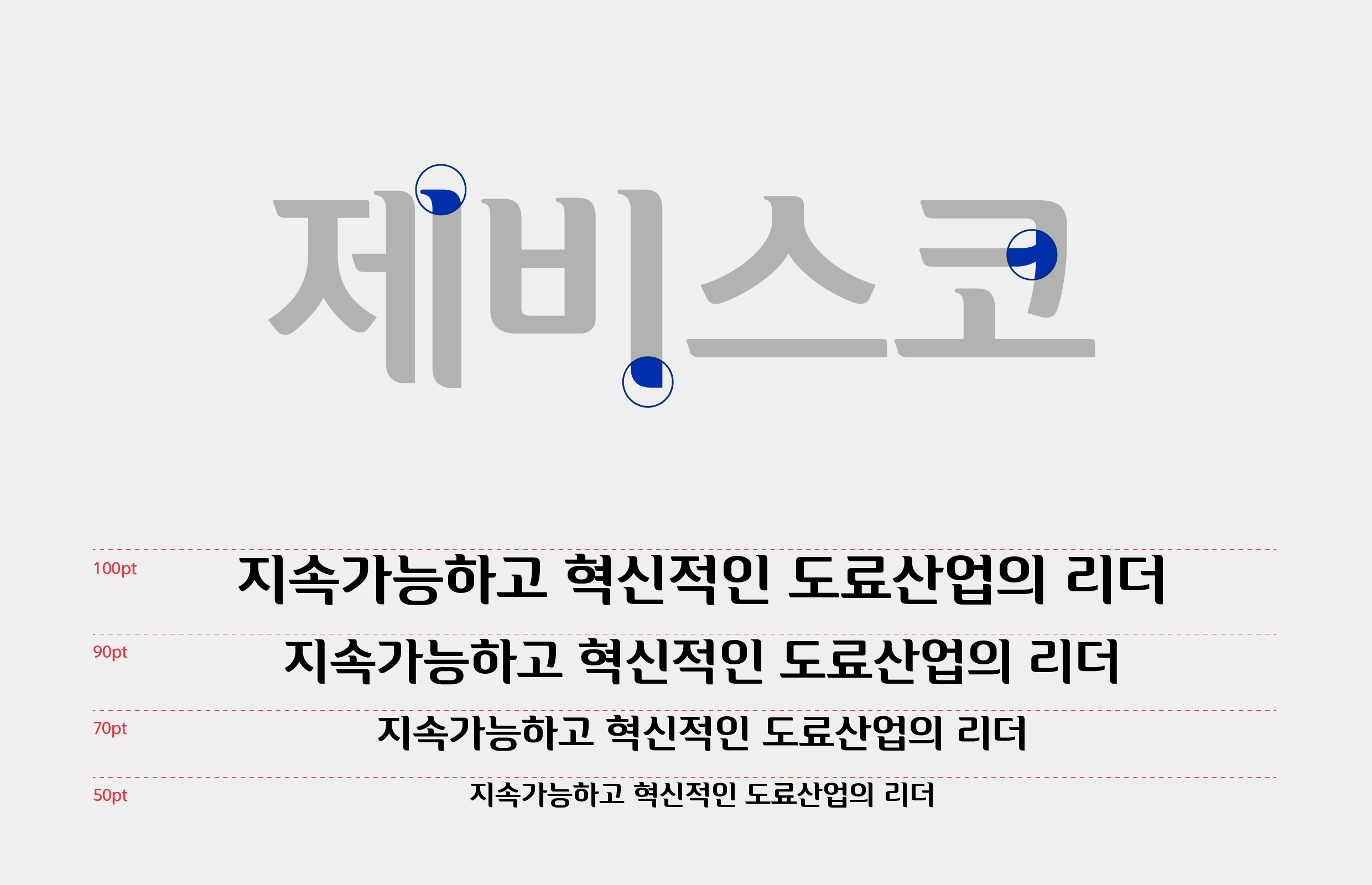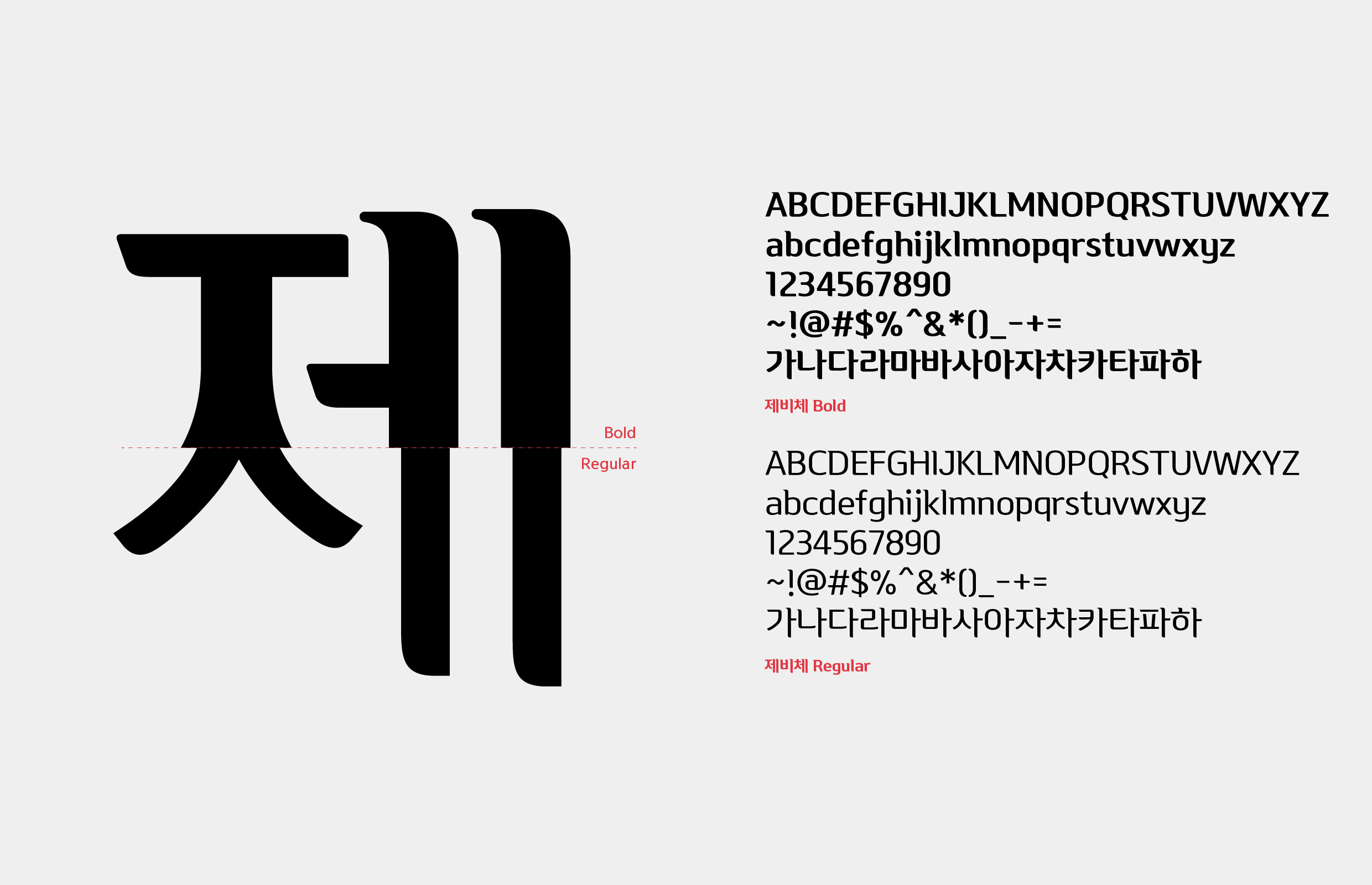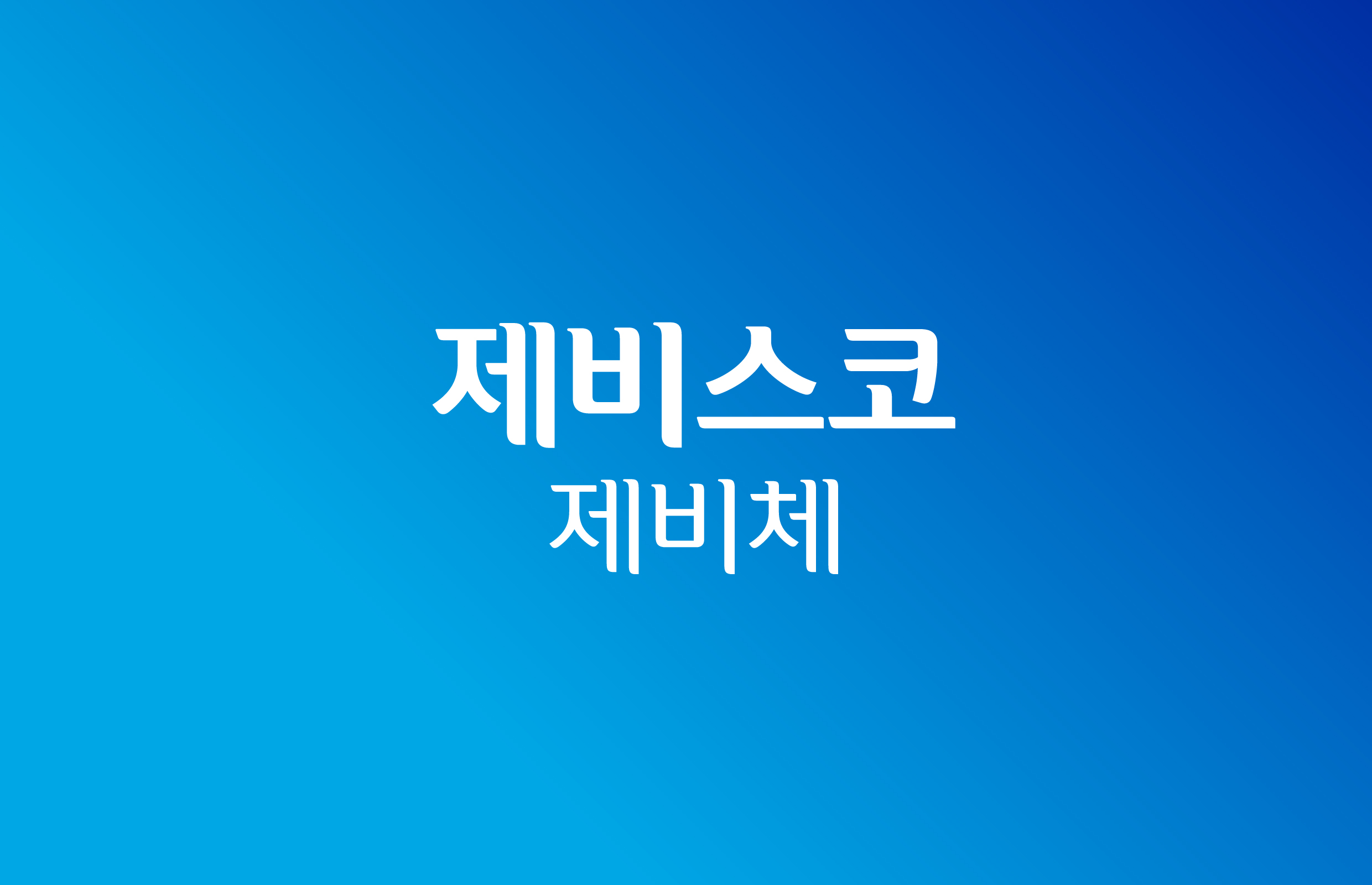
[]강남제비스코 [제비스코]
강남제비스코 [제비체]
세계로 뻗어나가는 진취적인 건설화학공업의 기업상을 기반으로 디자인했다. 꽉 찬 네모틀 구조로 설계하여 시원한 속공간을 가지며, 자소의 형태를 세련되고 모던하게 표현함으로써 안정적이고 든든한 기업의 이미지를 표현했다. 획의 비상하는 듯한 사선과 샤프한 형태의 세리프, 감성적인 곡선을 자소에 유니크하게 표현했다.